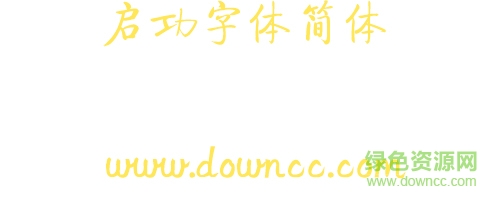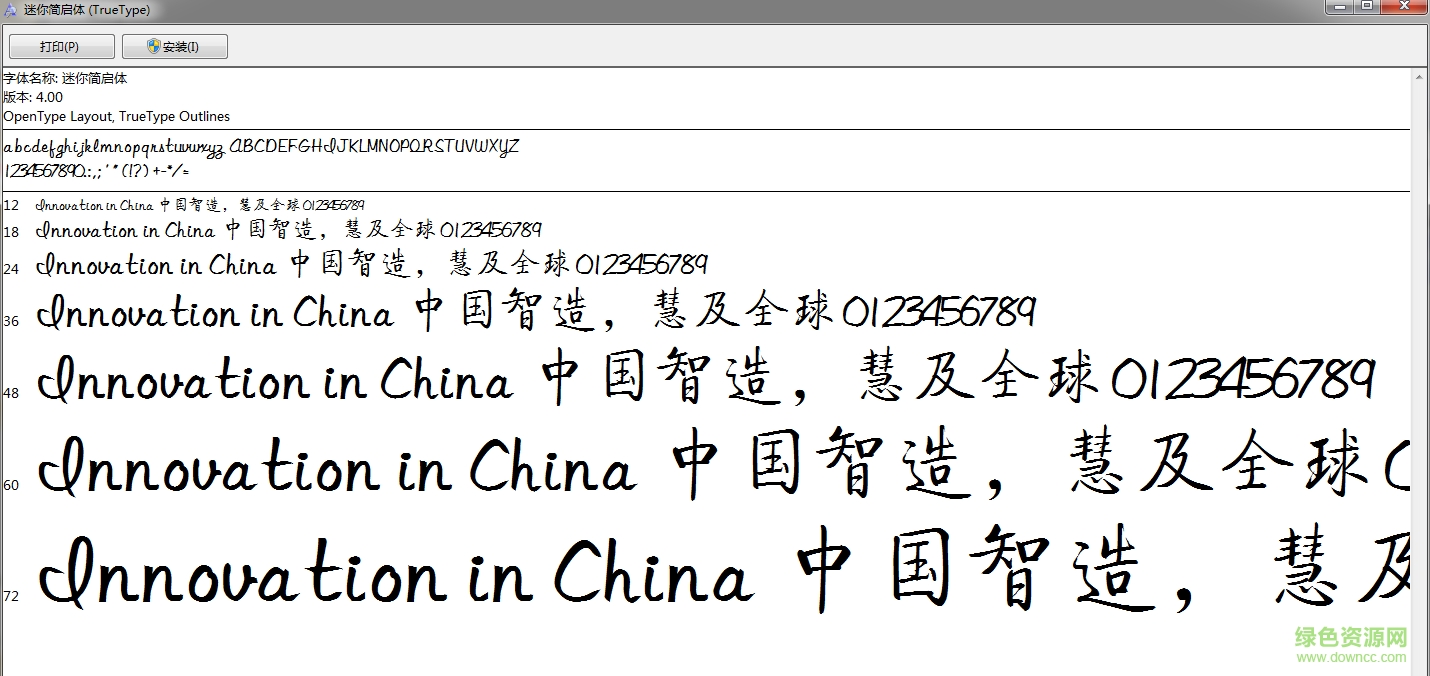
啟功字體簡體下載安裝后你就可以使用這一款仿照啟功字體樣式制作的字體文件,將啟功大師的字跡完美的再現(xiàn),歡迎喜歡的朋友前來下載使用。
啟功選擇一生貢獻非常大,他是中國當代著名書畫家、教育家、古典文獻學家、鑒定家、紅學家、詩人,國學大師。特別是在書畫領域有著非凡的名氣,啟功體一直讓人愛不釋手,有著非常多的崇拜者。啟功字體轉換器提供簡體和繁體兩款字體供生成!